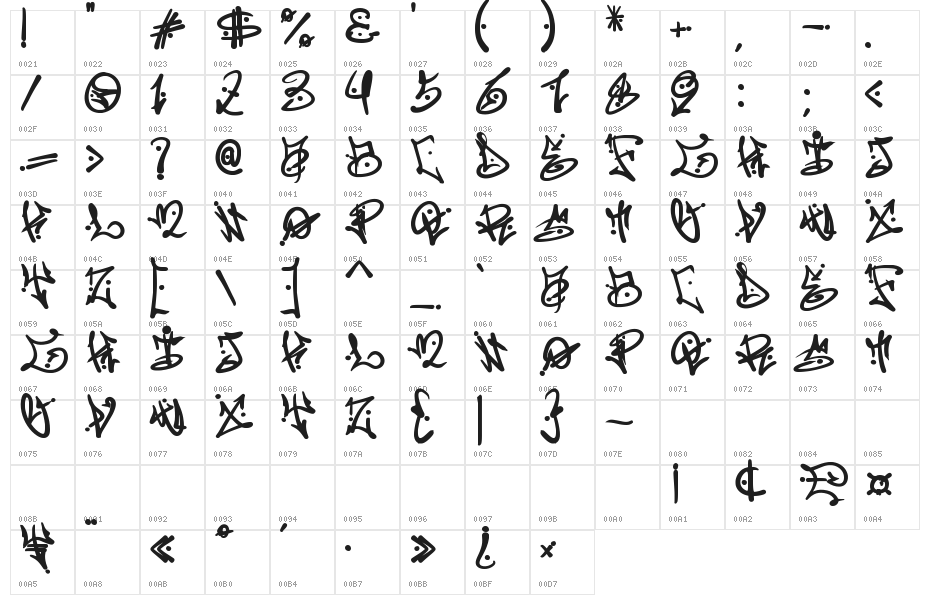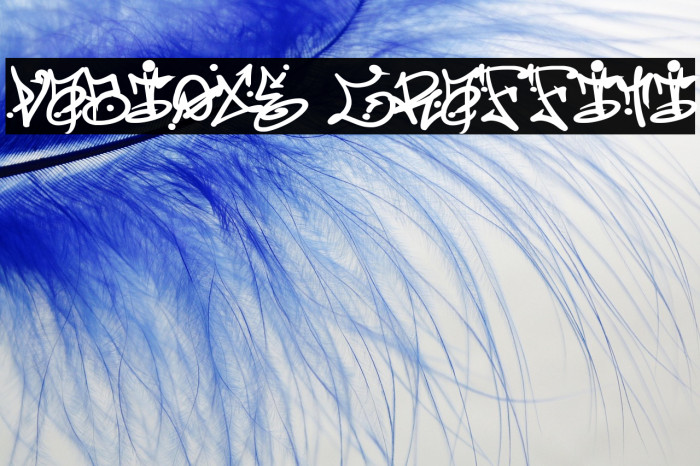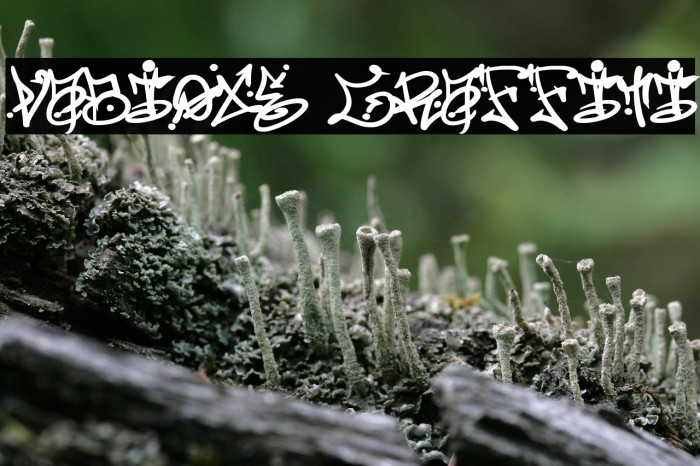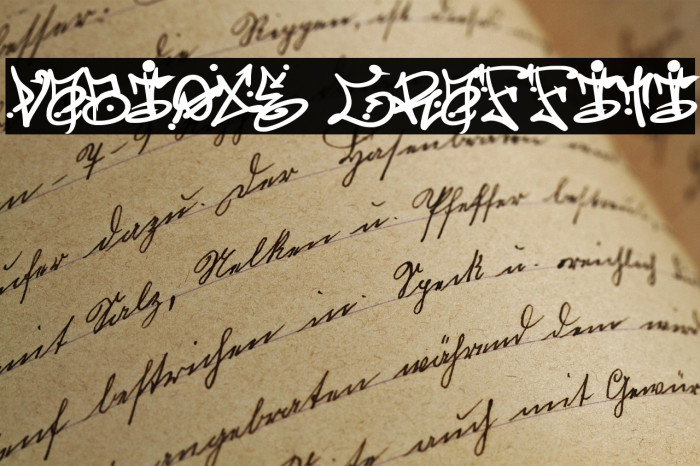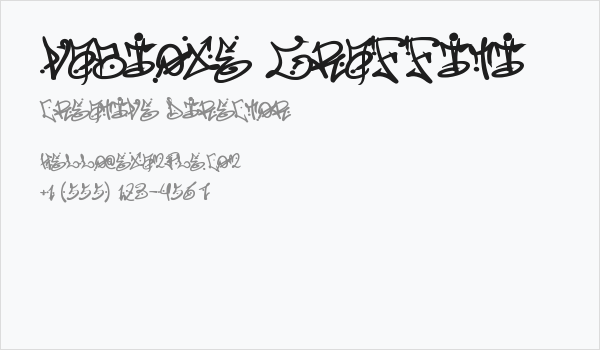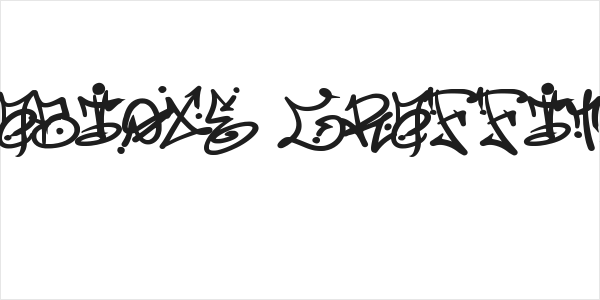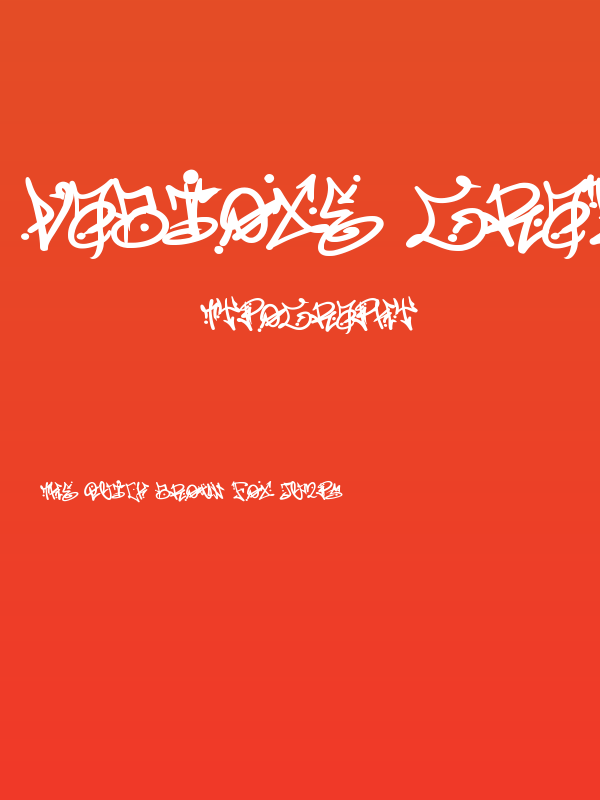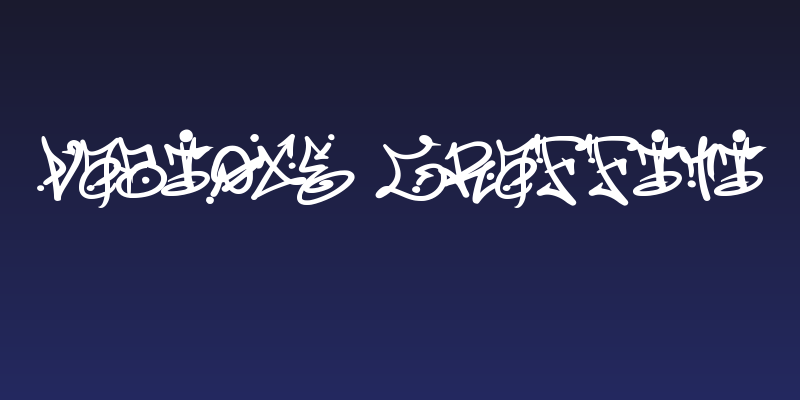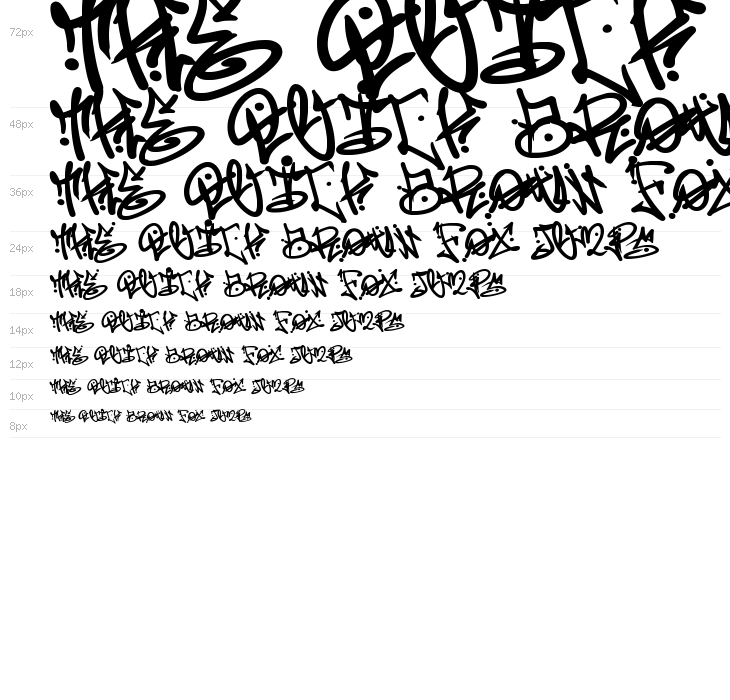
Vabioxe Graffiti Font
| Categorie | Graffiti |
| Stile generale | Urban, Edgy, Artistic |
| Caso d'uso | Logos, Posters, Album covers |
| Progetti proposti | Ideal for street art-inspired designs, music album covers, urban-themed posters, and edgy branding projects. |